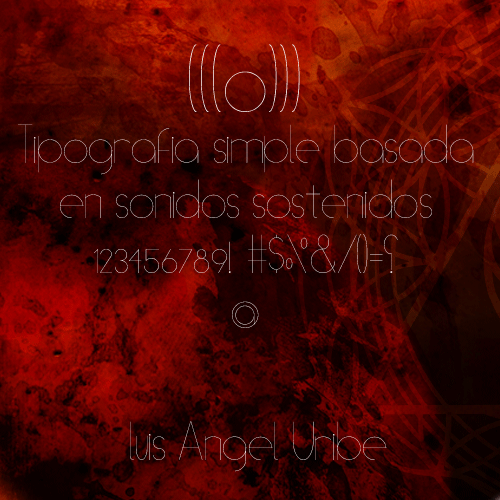
Preview and download (((O))) Basic Font. Created by Bichochos in Basic Sans serif styles with 100% Free license.
Font name: | (((O))) Basic |
Author: | Bichochos |
Note by Bichochos | |
tipografia simple basada en sonidos sostendos. O)))))))))))))))))))))))) |